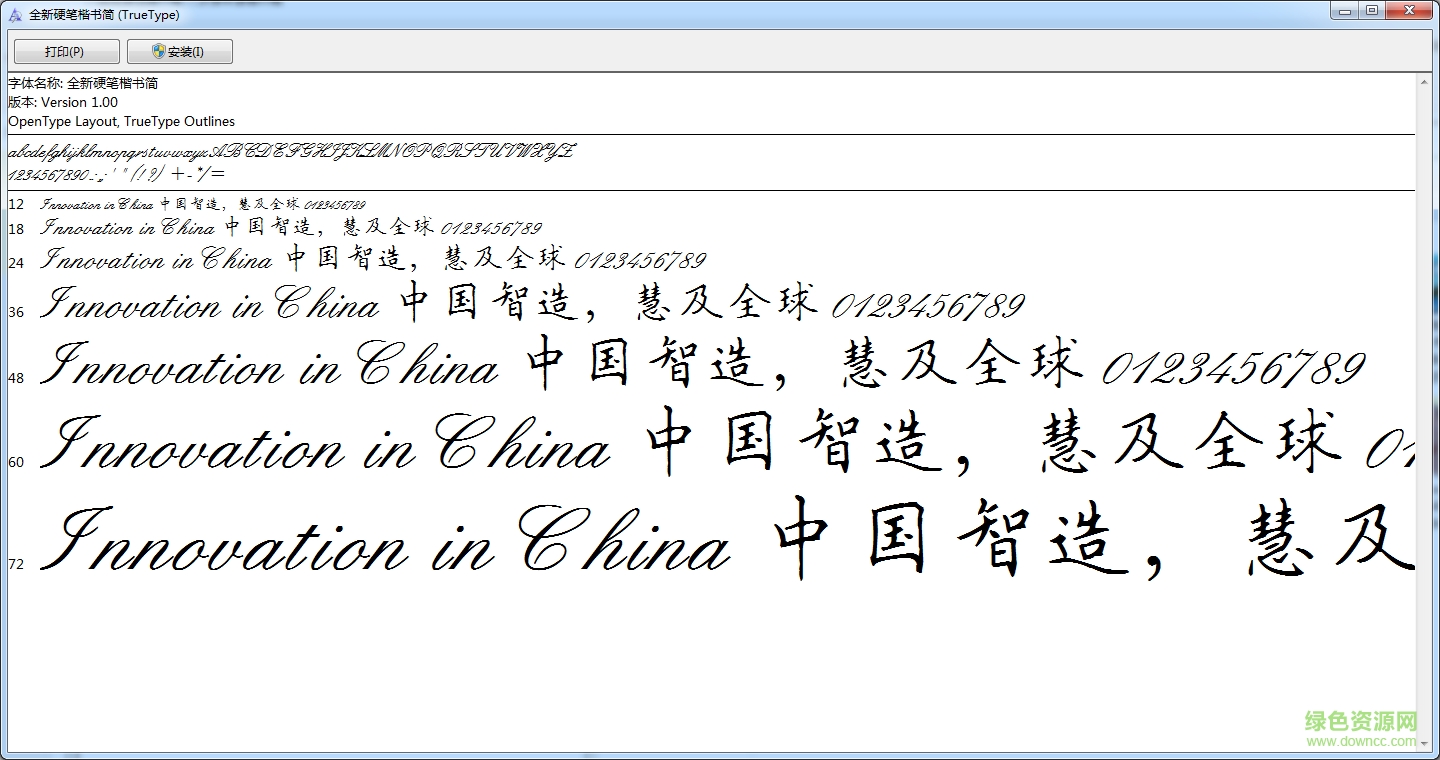
全新硬筆楷書(shū)簡(jiǎn)體是一款手寫(xiě)樣式的楷書(shū)字體,該字體中文端正典雅、英文輸入流暢大氣、數(shù)字輸入飄逸靈動(dòng),整體外形非常出眾,由隸書(shū)演變而來(lái),在日常設(shè)計(jì)中也是比較常見(jiàn),喜歡的朋友歡迎來(lái)綠色資源網(wǎng)下載!